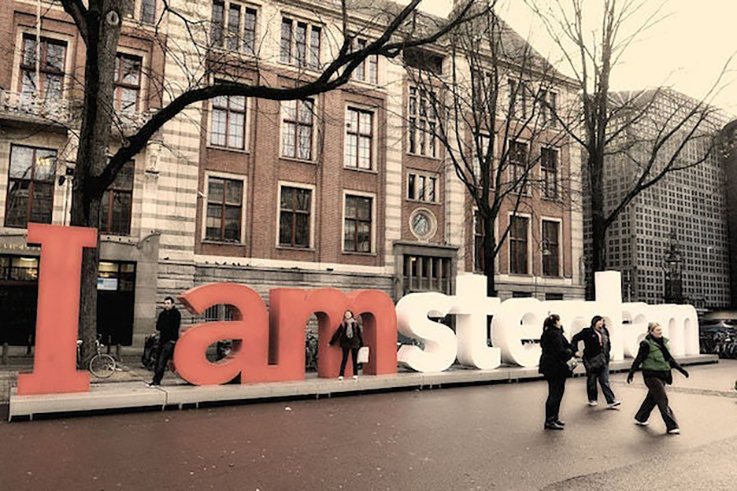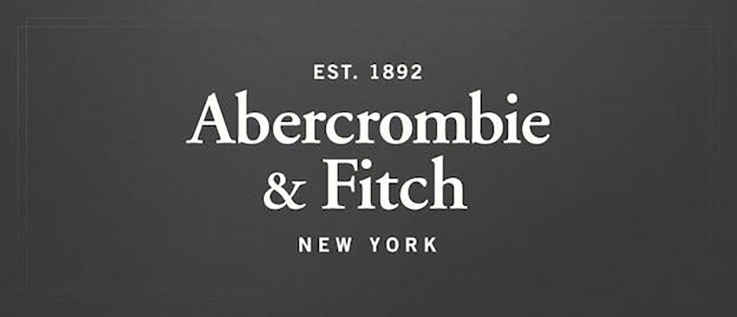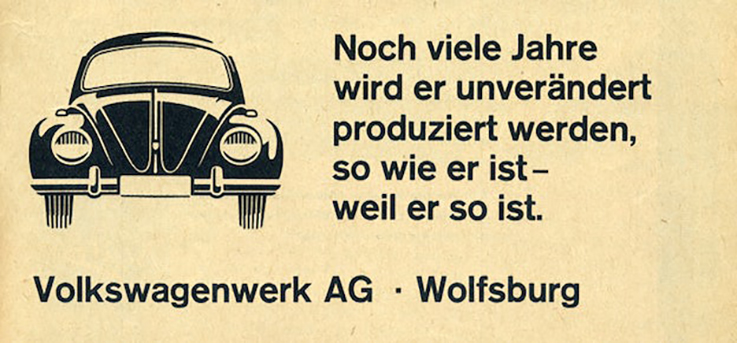
Lịch sử của 8 font chữ nổi tiếng thế giới.
Lịch sử của 8 font chữ nổi tiếng thế giới là những câu chuyện nguồn gốc các nhà thiết kế nổi tiếng thế giới đã tạo ra chúng.
Chúng ta hiện nay đã không còn xa lạ với những font chữ đã được cài đặt sẵn trên máy tính không chỉ nhân viên văn phòng mà các nhà thiết kế logo thương hiệu chuyên nghiệp sử dụng rất nhiều nhưng liệu bạn có biết đến lịch sử của 8 font chữ đã nổi tiếng trên thế giới được ai thiết kế và thiết kế như thế nào không. Hãy cùng xem bài viết sau để hiểu thêm lịch sử của những font chữ này nhé
Chúng ta cùng xem lịch sử hình thành các font chữ khi các phông chữ nổi tiếng nhất thế giới ở khắp mọi nơi. Mỗi phông chữ bạn thấy đều đi kèm với một câu chuyện, một người sáng tạo, một lịch sử và một cơ sở người hâm mộ. Khi bạn trở thành một nhà thiết kế, các serifs và trọng số dòng này bắt đầu xuất hiện và bạn bắt đầu nhận ra chúng trong khung cảnh.
Hãy xem một số phông chữ nổi tiếng này ra đời như thế nào và các nhà thiết kế đã thực hiện những bước táo bạo để tạo ra những gì sẽ tiếp tục thay đổi thế giới thị giác của chúng ta.
Helvetica
Font chữ Helvetica là một trong những font chữ không chân theo kiểu sans-serif được thiết kế bởi: Max Miedinger và Edouard Hoffman đã sử dụng rất nhiều trong các văn bản cũng như các thiết kế bao bì, thiết kế profile công ty…Được thiết kế tại xưởng đúc loại Hass tại Thụy Sĩ năm 1957. Ban đầu Miedinger muốn trở thành một họa sĩ, nhưng cha anh ấy nói với anh ấy rằng anh ấy cần tập trung vào một nghề thực tế hơn. Miedinger đã thiết kế kiểu và tạo ra Helvetica cùng với Hoffman 30 năm sau. Nó nhằm đáp ứng nhu cầu về một phông chữ trung tính, hiển thị rất tốt tại các biển chỉ dẫn, catalogue, văn bản... Đây được coi là một font chữ được sử dụng nhiều nhất trên thế giới. Nổi bật trong bộ phim Helvetica. Thương hiệu American Apparel…
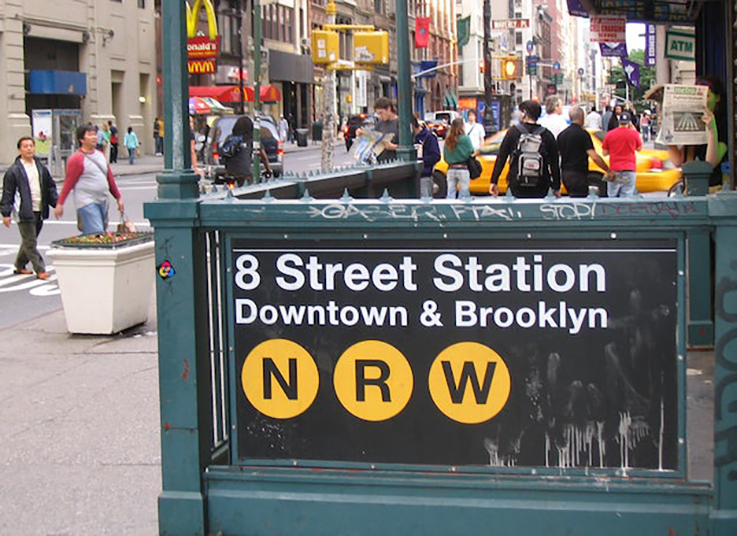
Font chữ Helvetica được sử dụng trên bảng chỉ dẫn
Bodoni
Font chữ Bodini được thiết kế bởi Giambattista Bodoni theo kiểu chữ serif tại Italia vào năm 1798 khi Bodini được thuê làm người sắp chữ chính thức cho một số công tước Ý. Những vị công tước này rất thích những tác phẩm và công việc của ông nên đã khuyến khích ông mở xưởng in tại cung điện ở Parma. Và ông đã được mệnh danh là "nhà thiết kế cho các vị vua và vua của các nhà thiết kế". Sau khi ông qua đời, các tác phẩm sắp chữ của ông đã được kết hợp để tạo ra phông chữ mà ngày nay chúng ta thường gọi là Bodoni.
Tuyên bố về sự nổi tiếng: Một trong những kiểu chữ cũ vẫn được sử dụng làm phông chữ ngày nay. Tạp chí Vogue. Mamma Mia! áp phích. Logo Nirvana. Columbia Records ‘wordmark.
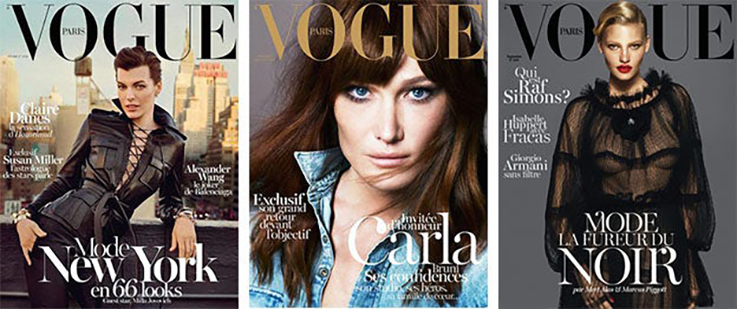
Font chữ Bodoni sử dụng trên các trang tạp chí
Times New Roman
Năm 1931 tại Anh font Times New Roman được thiết kế bởi Victor Lardent khi tờ The Times của Anh ủy quyền sau khi nhà thiết kế kiểu chữ Stanley Morison chỉ trích tờ báo vì tính dễ đọc của chúng. Morison đã hỗ trợ nhà thiết kế nội bộ Lardent để tạo ra phông chữ này được đọc nhiều trên toàn thế giới. Đây được coi là font chữ của văn bản toàn cầu, trên các bài báo, báo cáo...
Có trong mọi phiên bản của Microsoft từ năm 1992. Sử dụng thường xuyên trong sách báo. Tính dễ đọc cao làm cho nó tuyệt vời để sao chép. Không có danh sách phông chữ nào có thể hoàn chỉnh nếu không có nó.
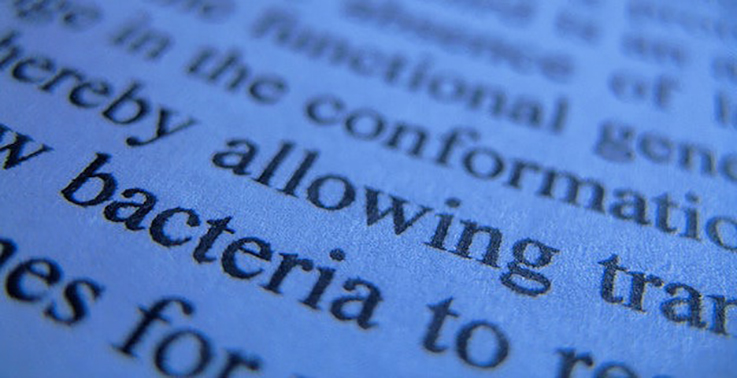
Futura
Font Futura là kiểu chữ sans – serif hình học được thiết kế bởi: Paul Renner tại Frankfurt, 1927 tại Bauer Type Foundry. Font chữ Futura nổi tiếng bởi sự đơn giản và mang nét hiện đại vẫn được rất nhiều các công ty thiết kế sử dụng trong việc thiết kế logo, thiết kế bao bì, áp phích quảng cáo. Tuy nhiên, sự khác biệt đó thuộc về Erbar, một phông chữ từ xưởng đúc Ludwig & Mayer. Futura được tạo ra như một phản ứng đối với phông chữ phổ biến lúc bấy giờ này. Do xưởng đúc Bauer lớn hơn nhiều so với xưởng đúc Ludwig & Mayer, nên Futura là phông chữ đứng trước thử thách của thời gian.
Tuyên bố về sự nổi tiếng: Vô số áp phích phim, bao gồm Gravity, American Beauty, Gone Girl và Interstellar cũng như các chương trình truyền hình như Lost và Sesame Street. Được sử dụng độc quyền trong cuốn tiểu thuyết đồ họa rất được hoan nghênh Watchmen. Đây là phông chữ yêu thích của các đạo diễn nổi tiếng Wes Andersen và Stanley Kubrick và thường được xuất hiện trong các bộ phim của họ.
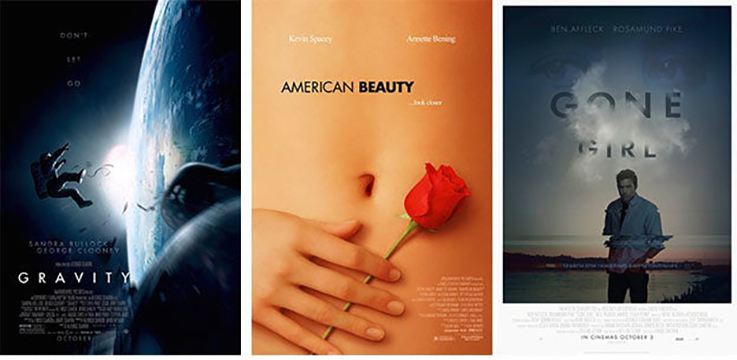
Font chữ Futura sử dụng trong các poster quảng cáo
Frutiger
Frutiger, một nhà thiết kế người Thụy Sĩ, được ủy quyền bởi xưởng đúc Mergenthaler Linotype của Hoa Kỳ. Khi họ muốn có một phiên bản in của kiểu chữ Roissy mà ông đã tạo ra cho bảng chỉ dẫn tại sân bay Charles deGaulle mới ở Paris. Frutiger tin rằng phông chữ có độ rõ ràng và mang nét hiện đại dễ dàng sử dụng in ấn trên mọi chất liệu, độ nhận biết cao.